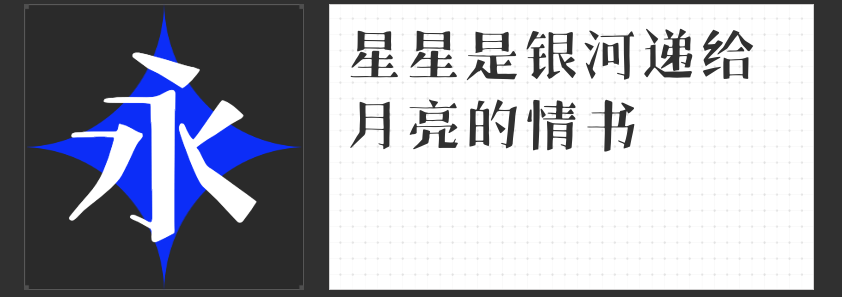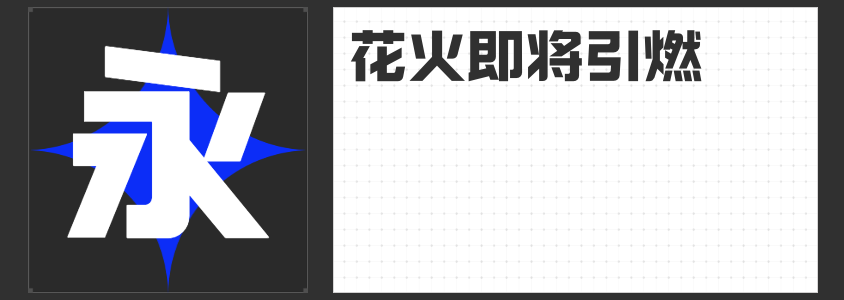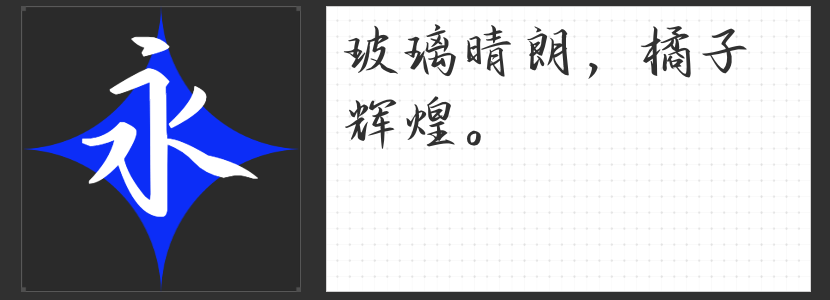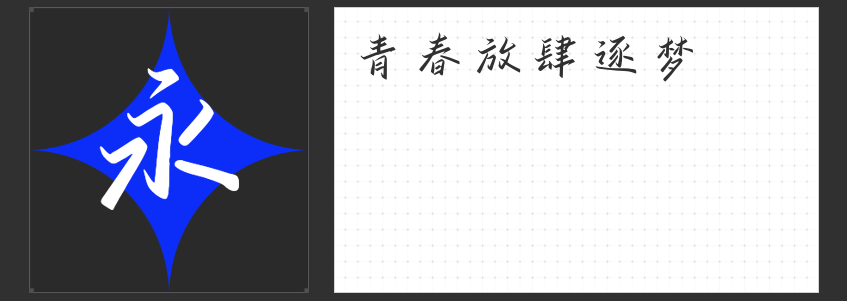
被《九部的检察官》氛围吸引?四款字体轻松打造悬疑剧视觉焦点
悬疑剧以其扣人心弦的情节、紧张刺激的氛围深受观众喜爱。字体作为视觉传达的重要元素,在营造剧集氛围方面扮演着至关重要的角色。推荐四款适用于“悬疑”氛围的电视剧设计中的字体。
1.励字勇敢黑简 特黑
“励字勇敢黑简 特黑”是一款充满力量感的无衬线字体。它的笔画厚重而有力,给人一种坚定且不可动摇的感觉。这种风格非常适合用来表达悬疑剧中的紧张气氛,可以有效地吸引观众的注意力。作为海报或电视剧Logo的主要字体,它能够迅速建立起一种神秘而又严肃的基调,非常适合《九部的检察官》这类题材。
2.高手庆科手绘宋
“高手庆科手绘宋”则是一款带有手绘风格的宋体字体。不同于传统的宋体,它通过手绘的方式呈现出一种独特的质感,仿佛每一笔都蕴含着故事的秘密。这种字体非常适合用于悬疑剧中涉及重要线索或关键信息的展示,能够增加一份神秘莫测的感觉。将其运用在海报设计上,不仅能凸显出剧集的主题,还能激发观众的好奇心。
3.字青春逐梦简 准粗
“字青春逐梦简 准粗”是一款略带圆润感的无衬线字体,它的笔画既有一定的重量感又不失流畅性。这种字体给人一种积极向上、充满活力的感觉,适合用来表现剧中人物对正义的执着追求。它既可以用作电视剧Logo的核心字体,也可以用于宣传语的呈现,能够有效地传递出正义终将战胜邪恶的信息。
4.也字工厂川秋沙行楷
最后要推荐的是“也字工厂川秋沙行楷”。这款字体采用了行楷风格,笔触流畅自然,带有一种书法般的美感。它既保留了传统书法的魅力,又融入了现代设计的元素,非常适合用于营造悬疑剧中的文化氛围。将这款字体用于电视剧的标题或者宣传材料中,能够给观众留下深刻印象,同时也能增添几分文艺气息。
综上所述,这四款字体各具特色,可以根据不同设计需求来灵活运用。无论是需要营造紧张氛围、增添神秘色彩、传递正能量还是增加文化韵味,这些字体都能为剧集的设计增添不少亮点。希望今天的推荐能够为您的设计提供一些有用的参考和启发!